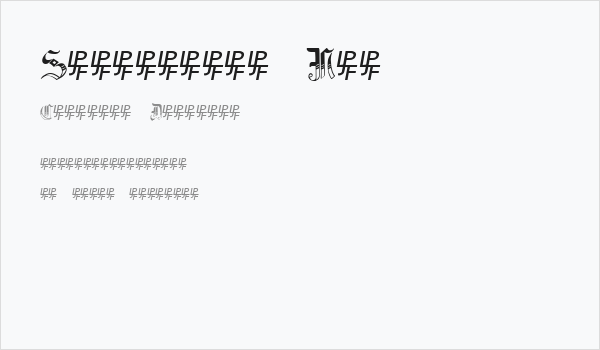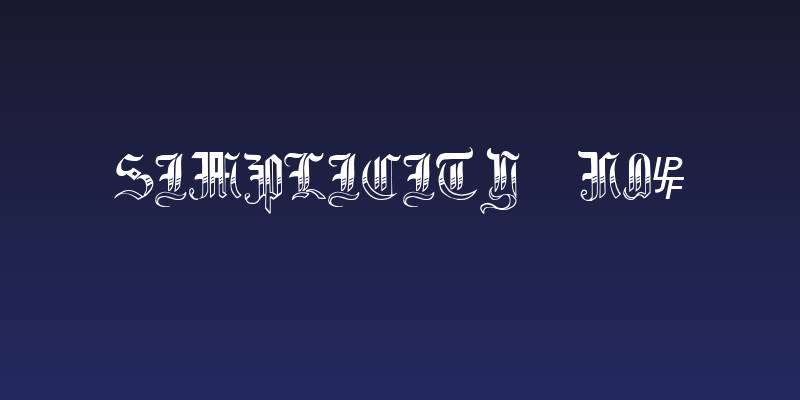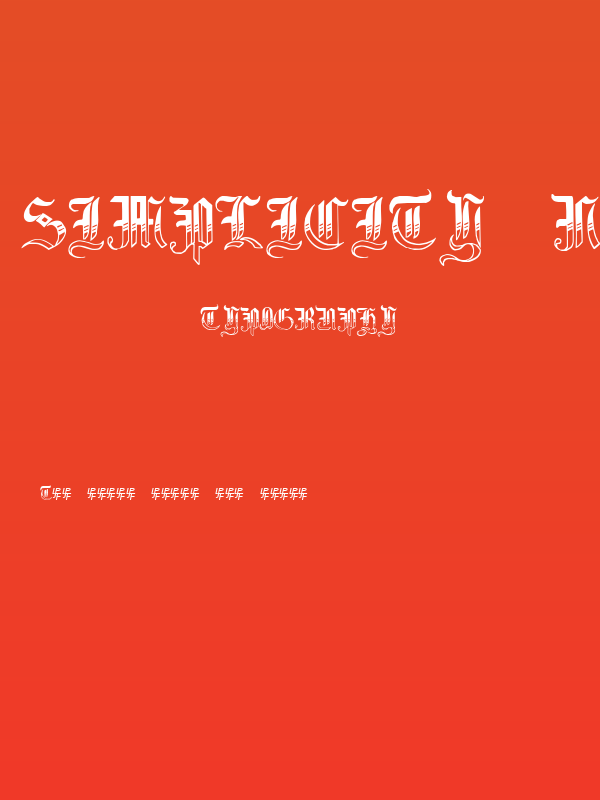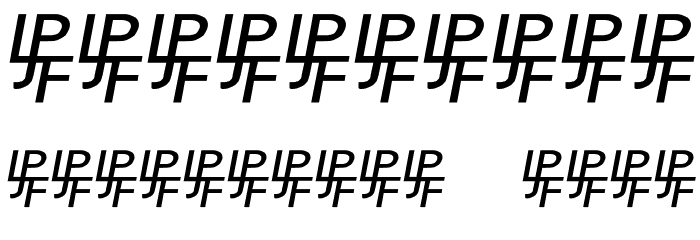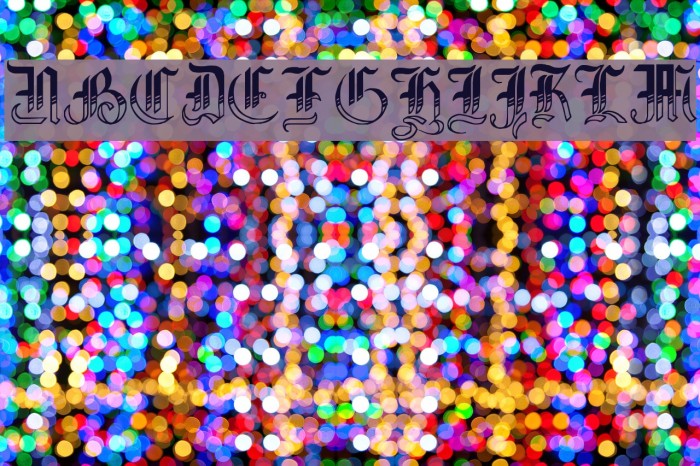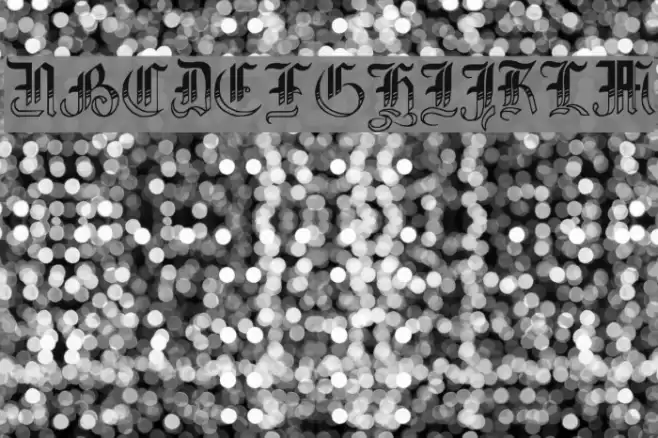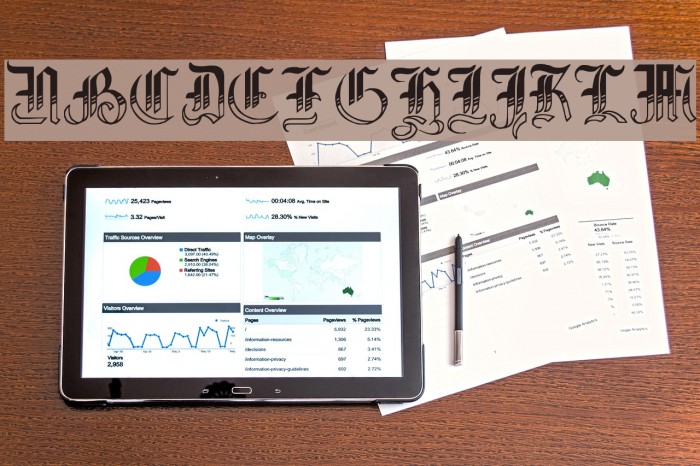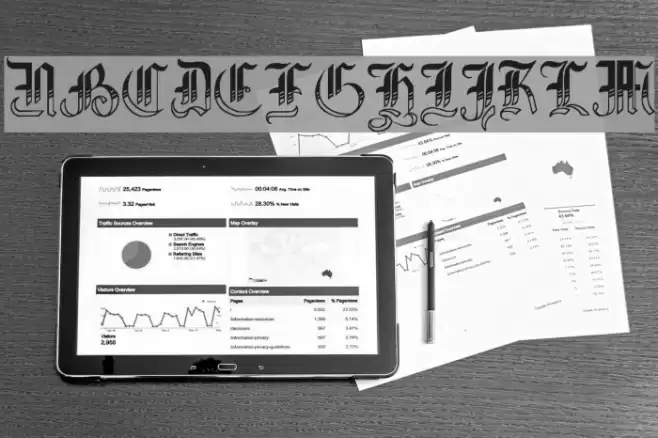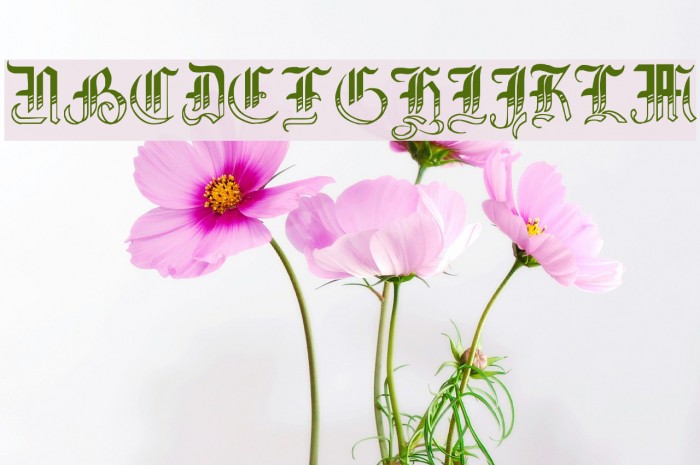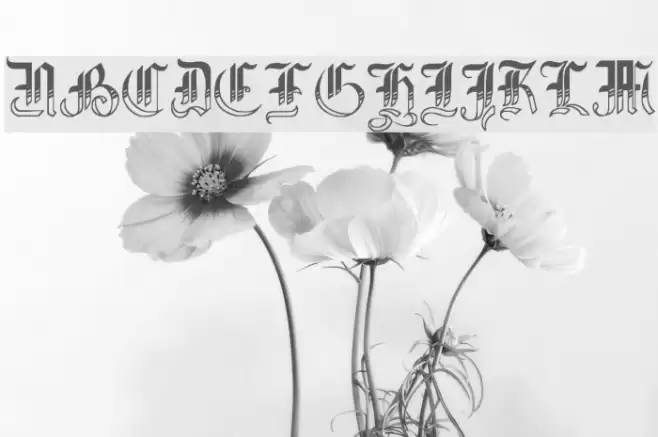
Simplicity No4 Font
✎ Gothic
Paul Lloyd Fonts
| Категория | Gothic |
| Общий стиль | Vintage |
| Область применения | Logos, Headlines, Decorative text |
| Рекомендуемые проекты | Ideal for projects that require a historical or medieval theme, such as book covers, posters, or branding for vintage products. |